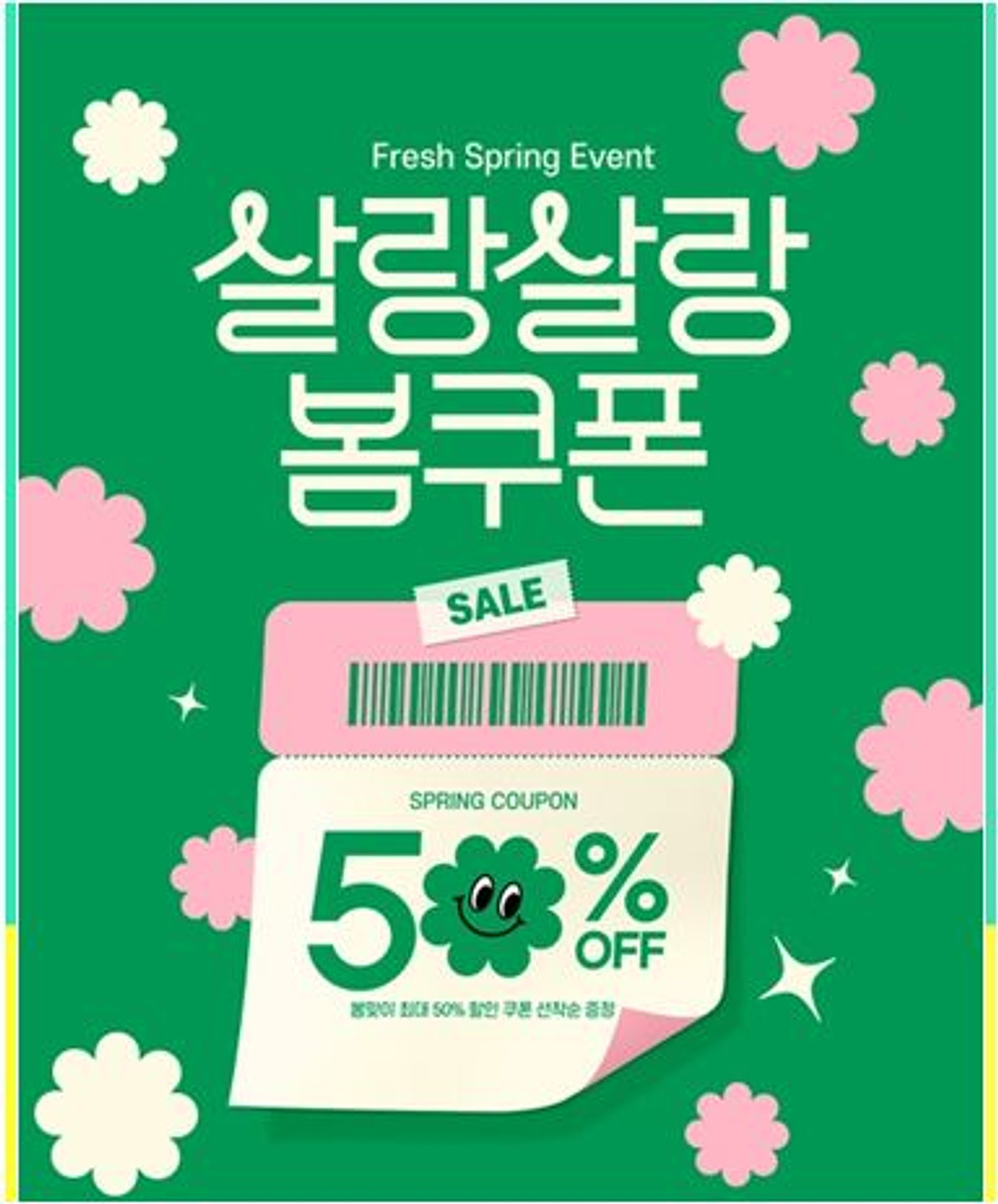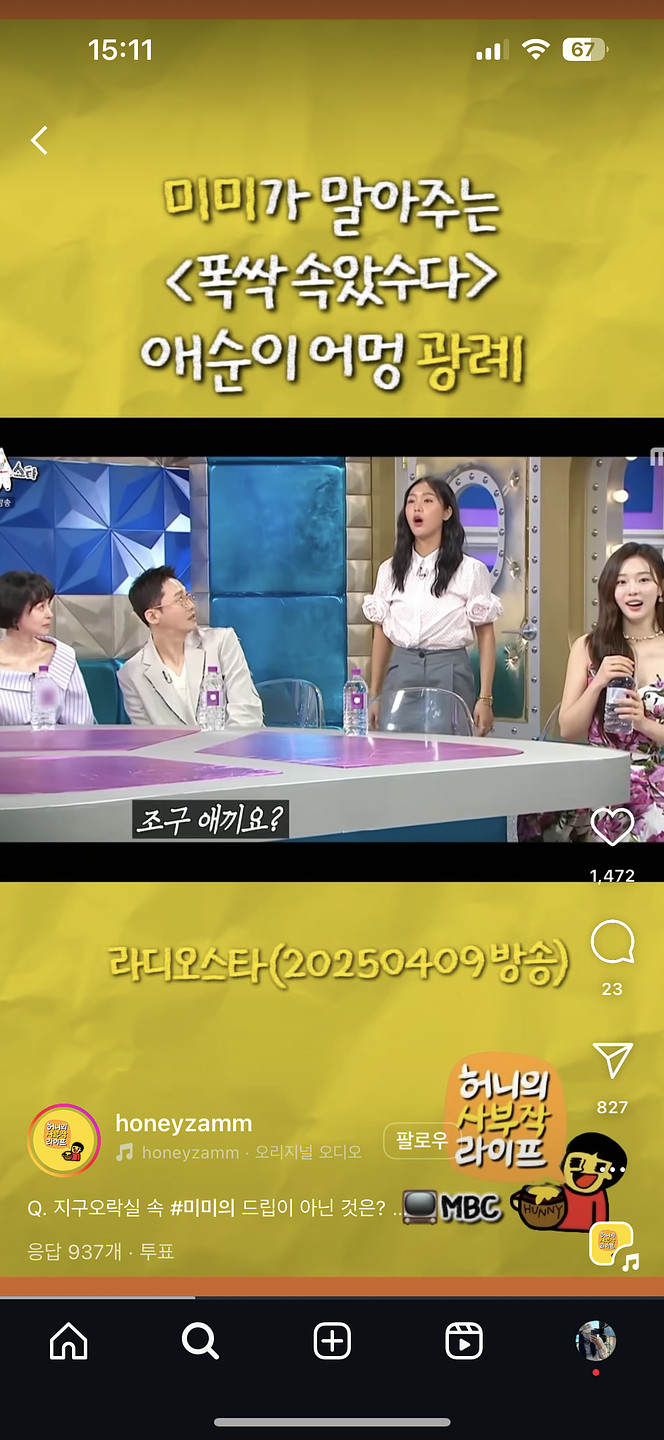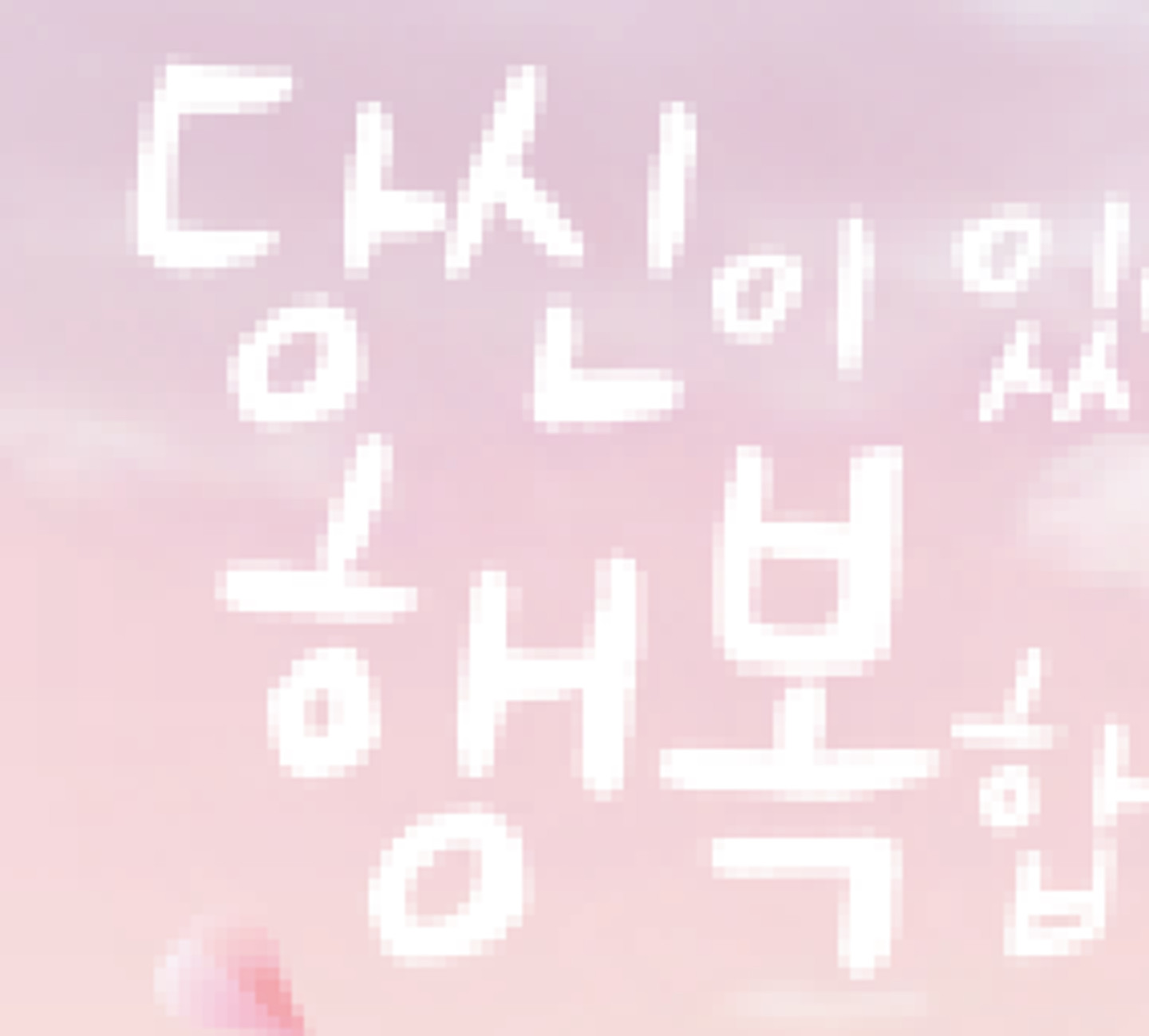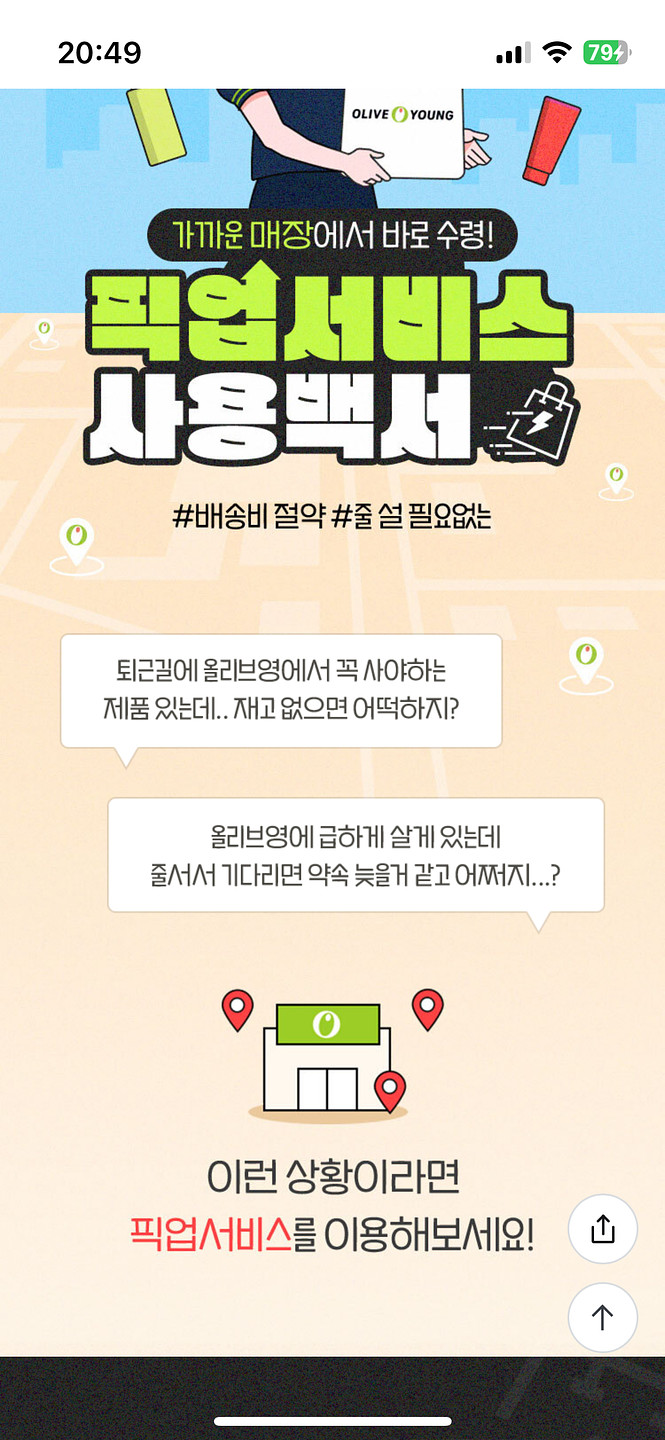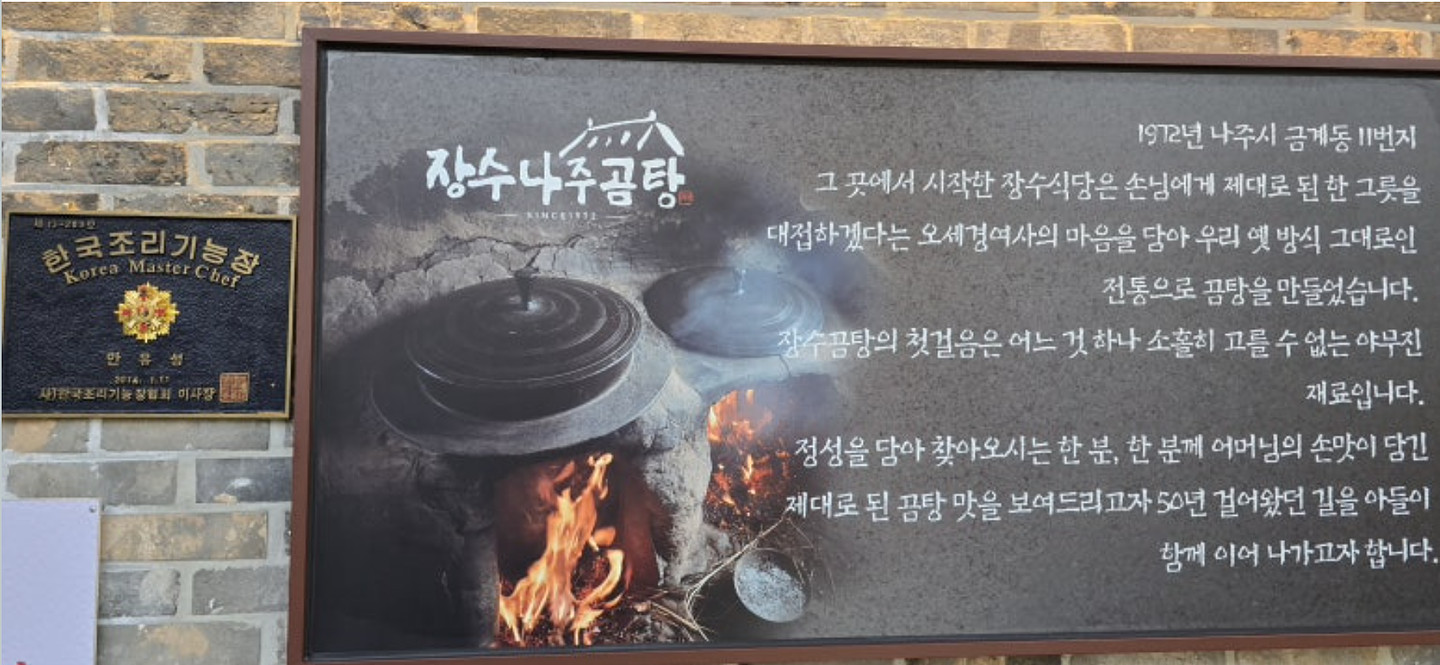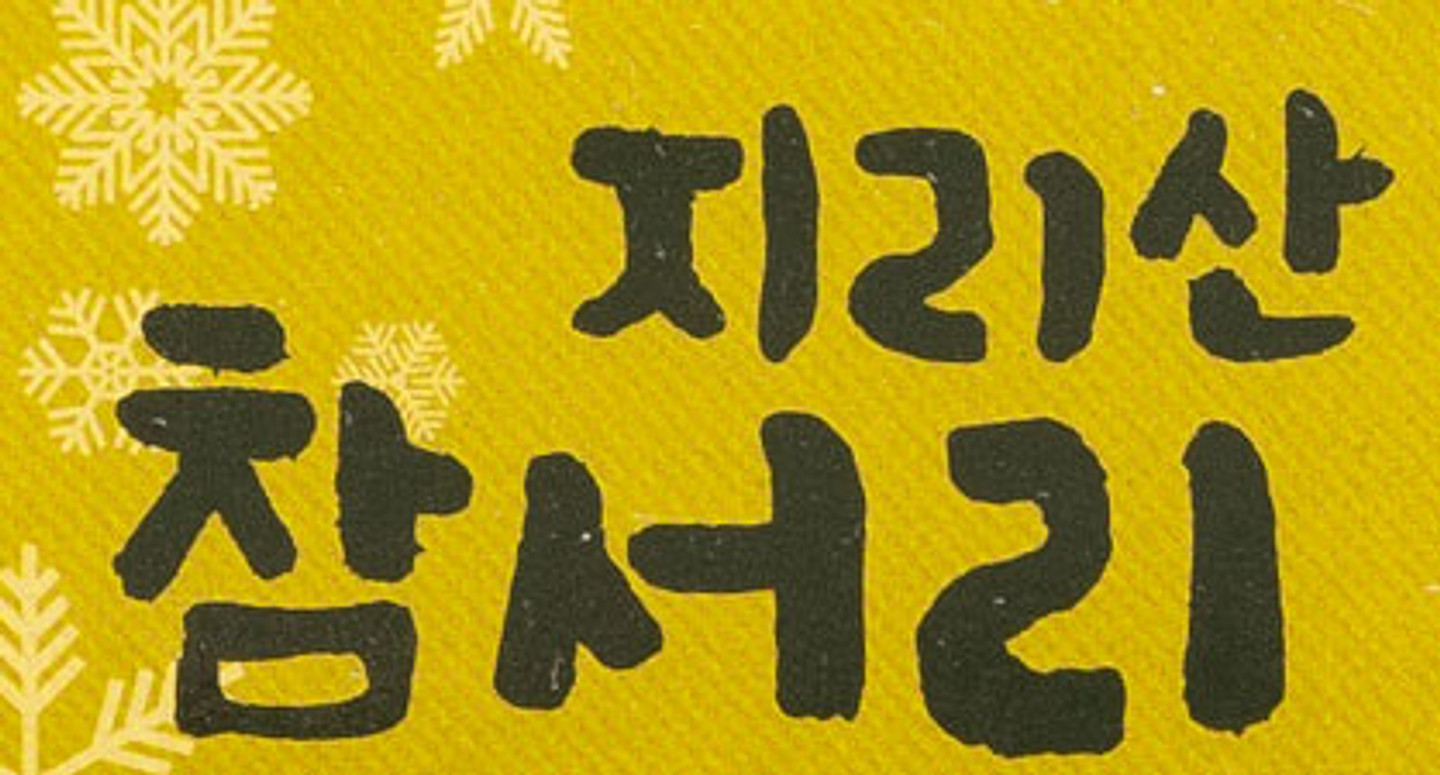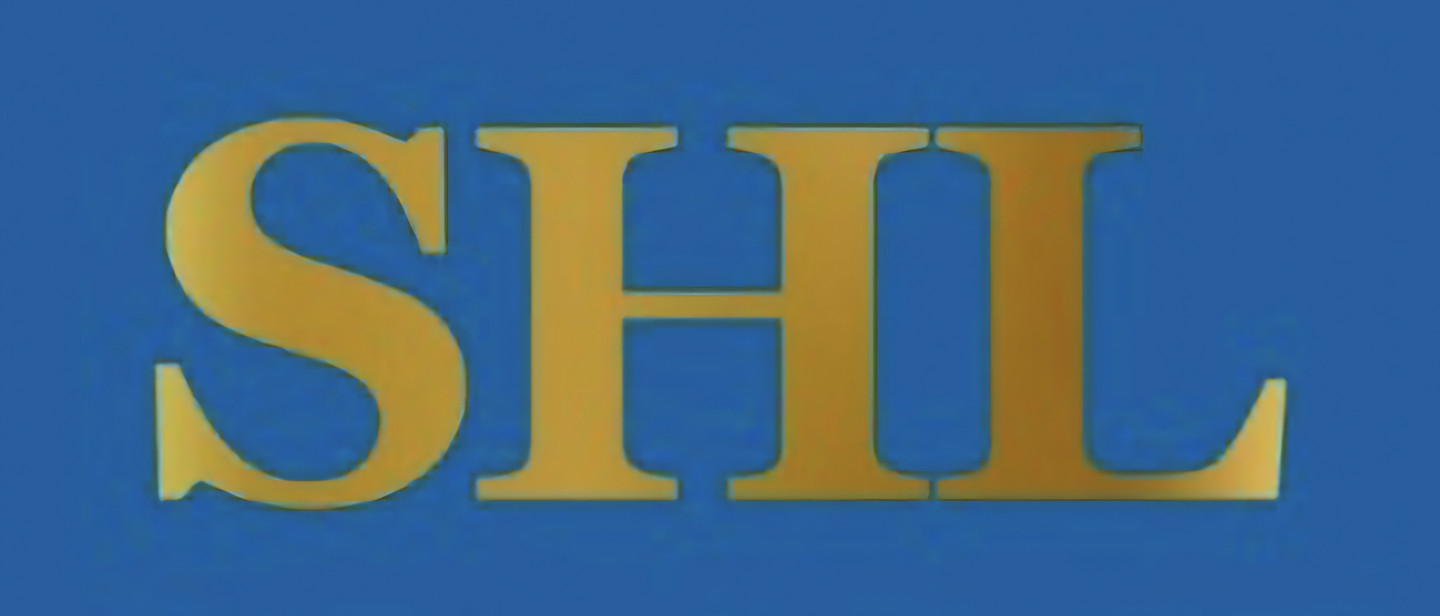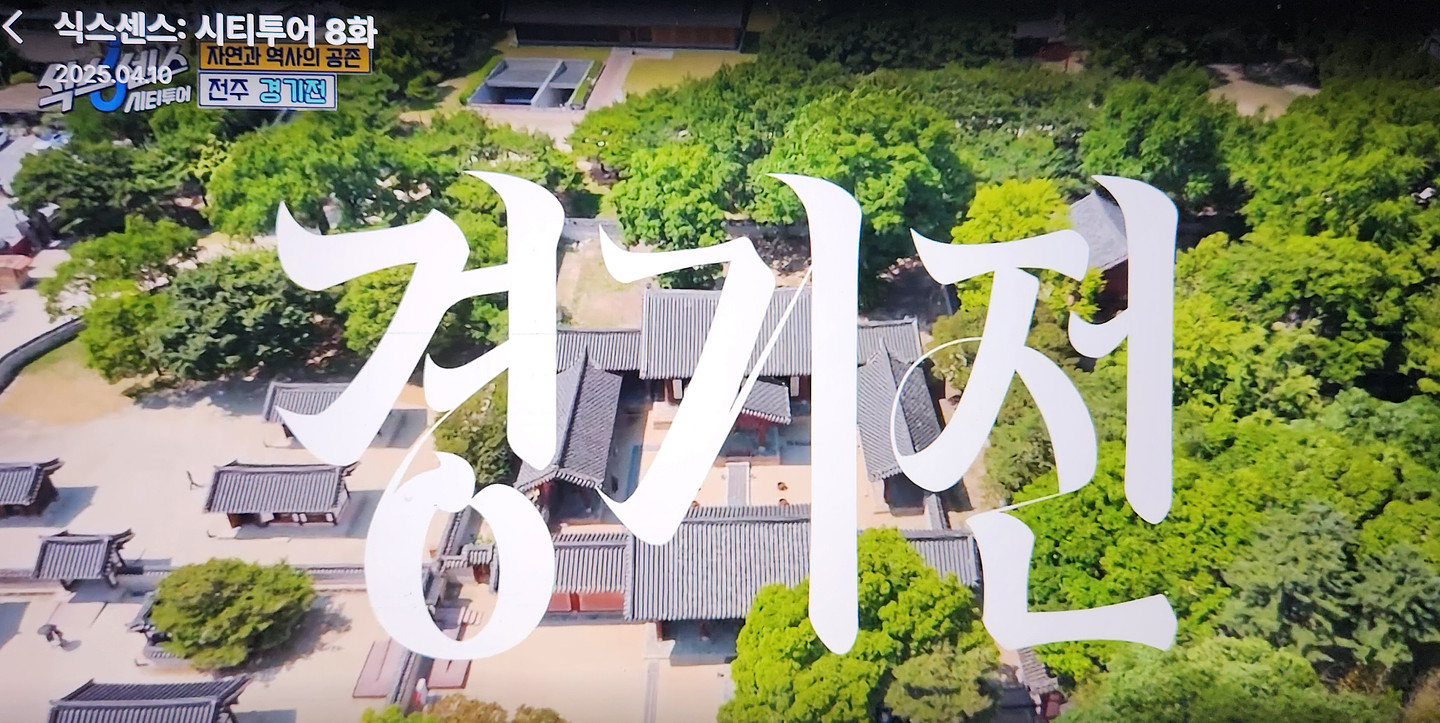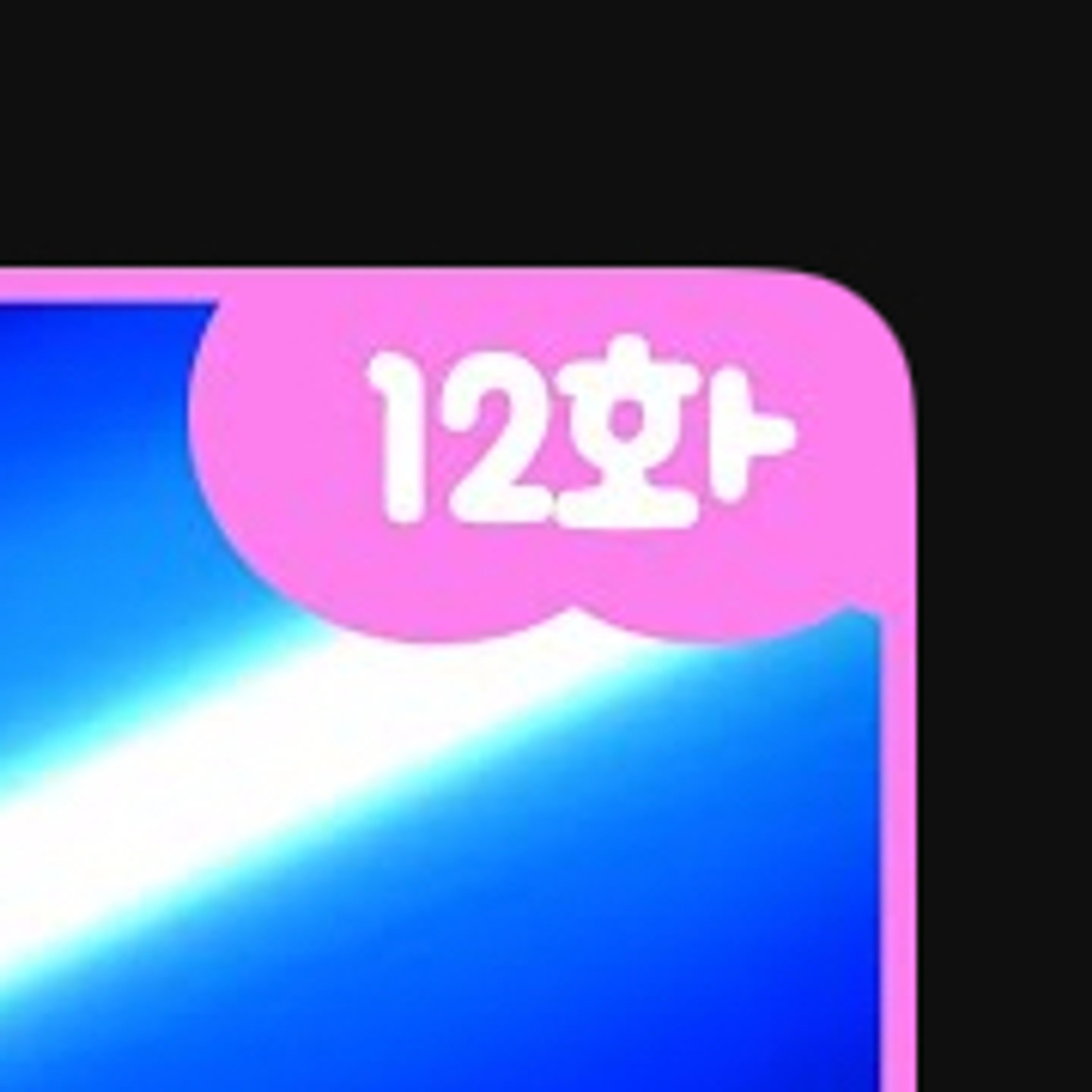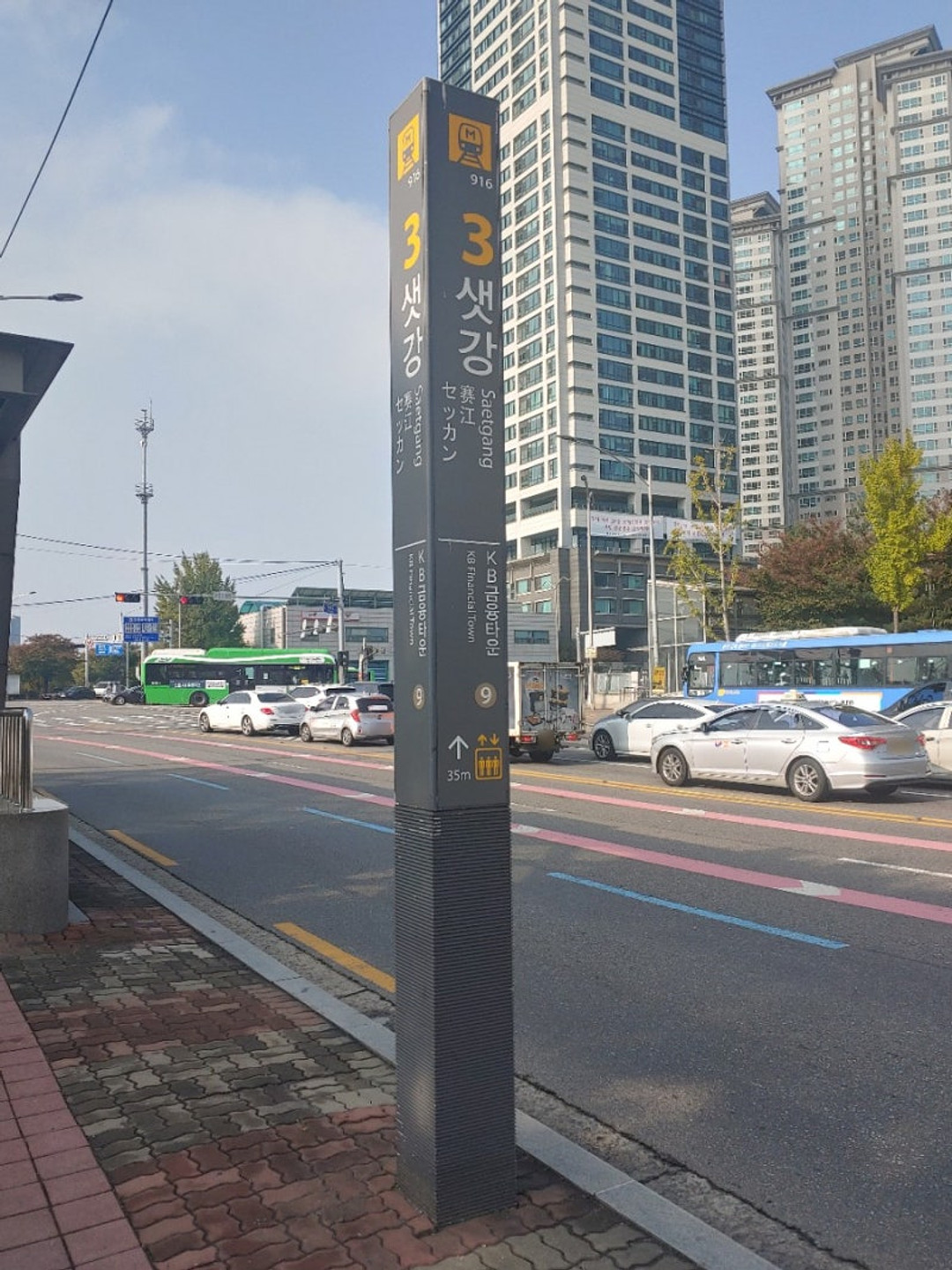
무슨 폰트인지 찾아주실수 있나요 ㅠㅠ 제가 봤을땐 HU슬로건같은데 HU슬로건이면 저 폰트들 제가 다 수정해야해서....... 혹시나 다른 무료폰트일수도 있으니까 희망을 가지고 여쭙니다 ㅠㅠ 도와주세여...
프리미어 작업하다가 에러나면서 폰트가 위사진말고 다른폰트로 무작위로 바꼇습니다... 원래 폰트명이 기억이 안나서 찾아보려니 도저히 잘 안보이네요ㅜㅜ 고수님들의 답신 부탁드립니다!!!
샤갈!!!!!! 무슨 폰트죠 나의 마음이 콩!!!!!닥????? 나를 한번에 사로잡은 폰트!!!!!! 샤갈!!!!! 쿵쾅쿵쾅!!!!! 저 이 폰트 찾아야 해요!!!!! 찾아야만해!!!!!
유튜브나 인스타에서 많이 보이는 영문필기체인데 비슷한거는 많이 봤는데 다 한끗차이로 달랐어요 ㅠㅠ 정확한 폰트 알고계신분 답볍바랍니다 🫶🏻